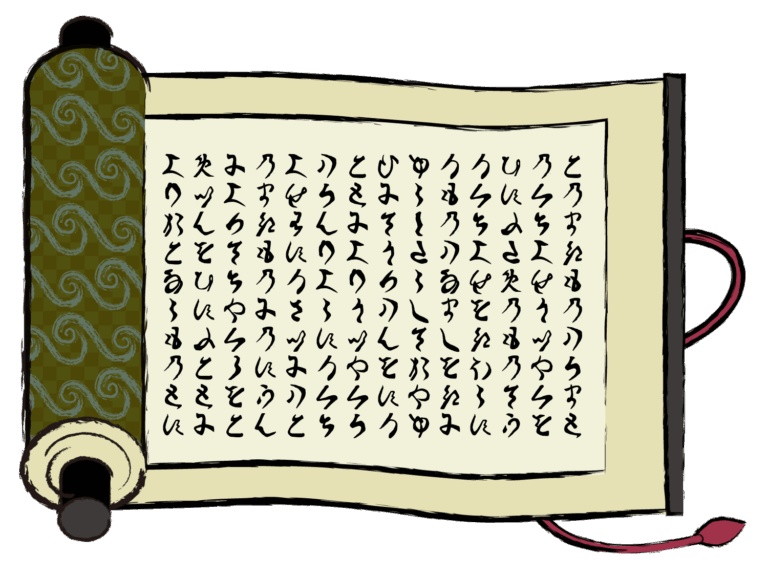
古文書崩し字かなフォント
NARUTOのコスプレ小道具「巻物」を作るにあたってこんなフォントがあったらいいな、というフォントを作りました。 敢えて全然読めないようにしています。 また、字は全て情報・システム研究機構の「くずし字データベース」を参照し、実際に古文書の中で使用されているひらがなのくずし字をフォントにしています。 雰囲気を崩さないために濁音、半濁音、句読点などは入っておりません。 巻物、掛け軸、書物などコスプレの小道具作り以外にも色々使用可能かと思います。 利用にあたって 商用利用の際はご連絡ください。 また、再配布はいかなる場合も禁止します。 使用は自己責任にてお願いいたします。 個人で使用する分には加工・改変は構いません。